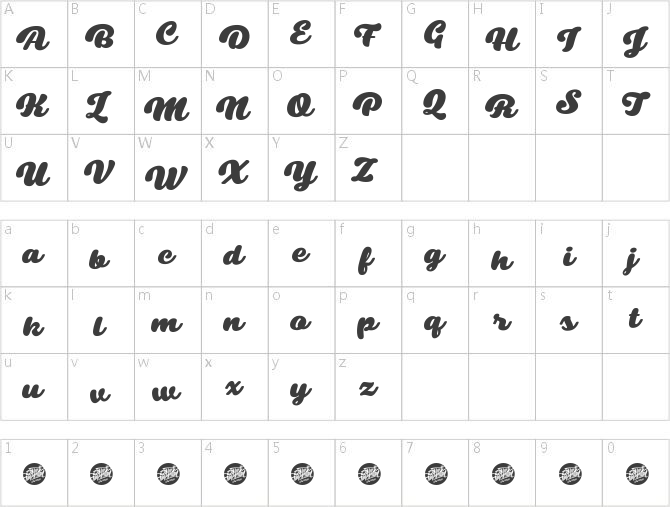
字體名稱: Swiftel
Swiftel Base DEMO
Swiftel Base DEMO介紹
Swiftel Base DEMO字體字庫是一款讓人賞心悅目、百看不厭的英文字體,適合各類廣告和產品包裝設計應用,字體大小0.02MB,格式為ttf字體,上傳用戶是浪遍塞納河的,作者/版權方為未知
Swiftel Base DEMO效果圖